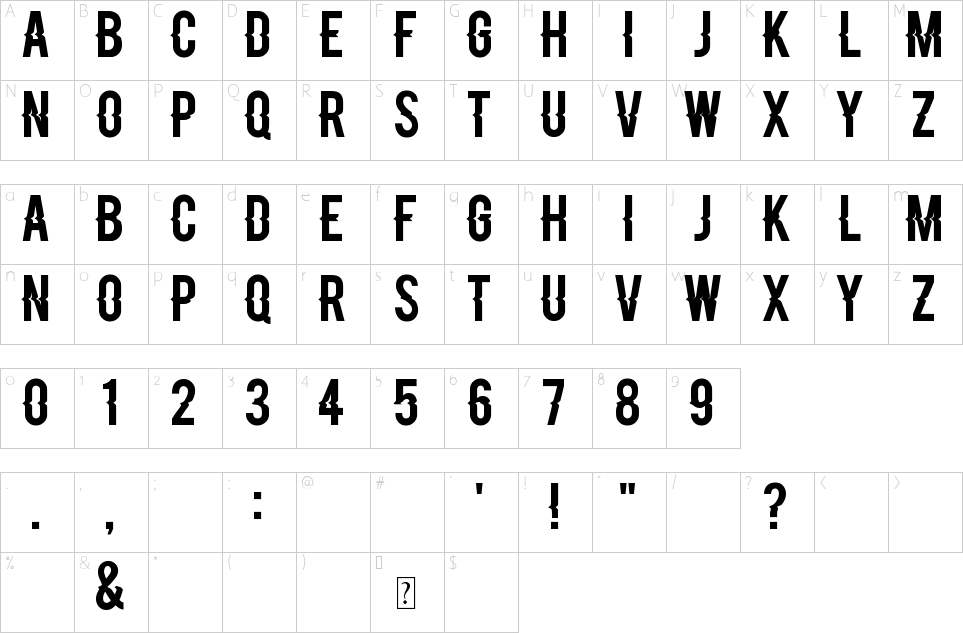
Descubra a elegância e os detalhes únicos da Blacklisted Font, uma graciosamente simples e sofisticada opção para seus projetos digitais. Desenvolvida por Jayde Garrow, esta fonte se destaca como um recurso inestimável para designers iniciantes e experientes. Com downloads contínuos ao longo de sua existência, a Blacklisted Font já recebeu mais de 91 mil utilização no Windows e Mac, mostrando o seu valor e estabilidade. Sua linhas clean, combinadas com um design cuidadosamente elaborado, garantem uma experiência visuais fluida e elegante em qualquer projeto. Ideal para aplicativos web, templates de apresentações ou até mesmo textos simples e diretos em sites pessoais, Blacklisted Font é perfeita tanto para a personalização quanto para uma estética que se destaca. Descubra por si mesmo, insira a beleza da Blacklisted na sua próxima criação digital.